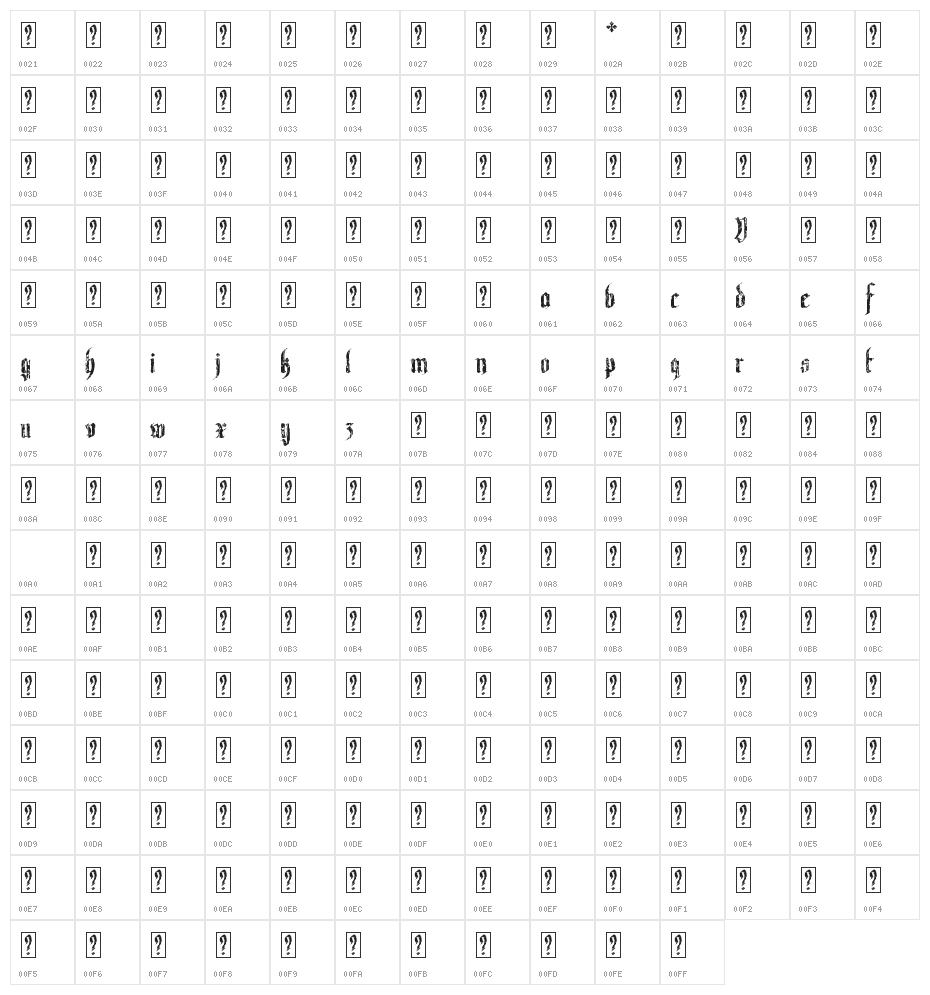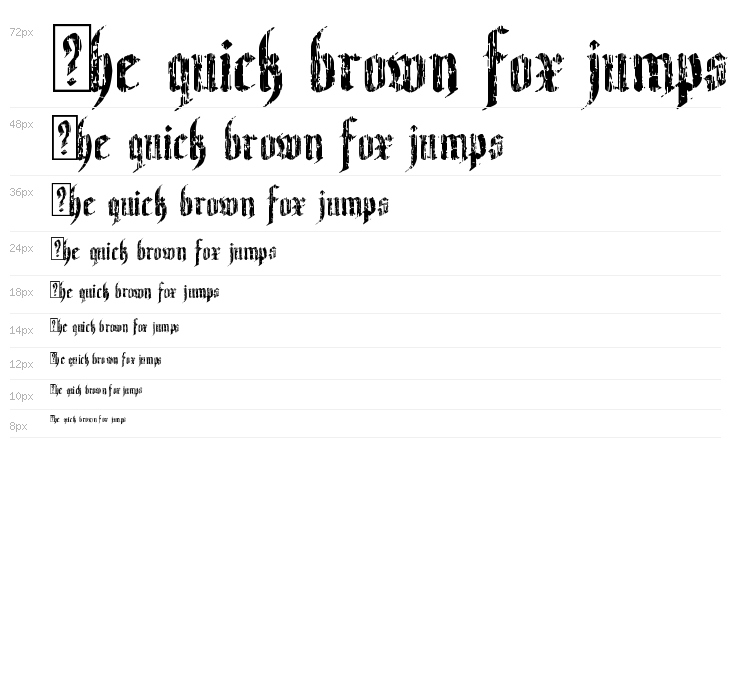
Varaninde Font
✎ Gothic
| Estilo general | Vintage, Gothic, Decorative |
| Proyectos propuestos | Ideal for album covers, posters, branding for alternative or gothic-themed events, and any design needing a vintage or edgy look. |